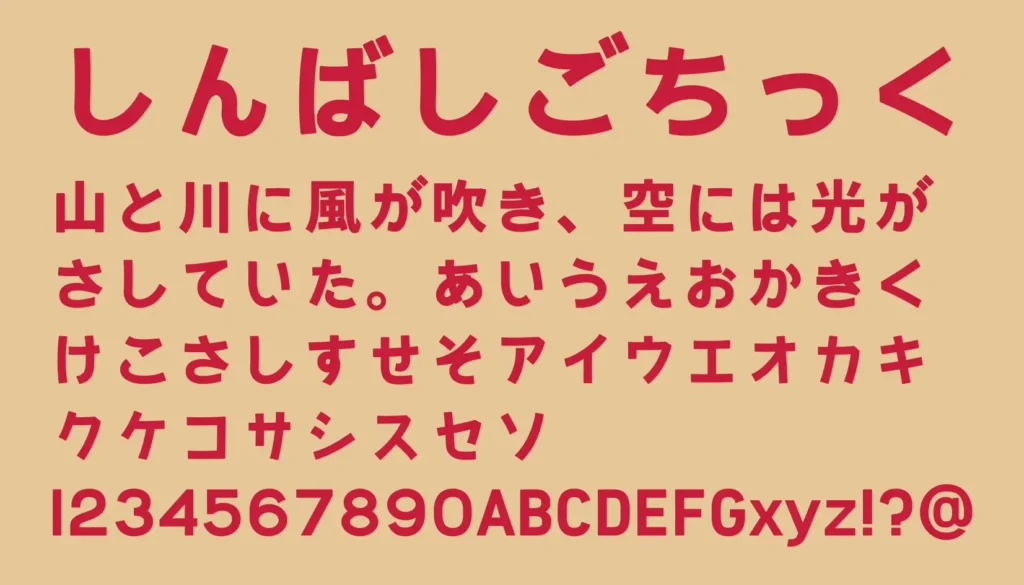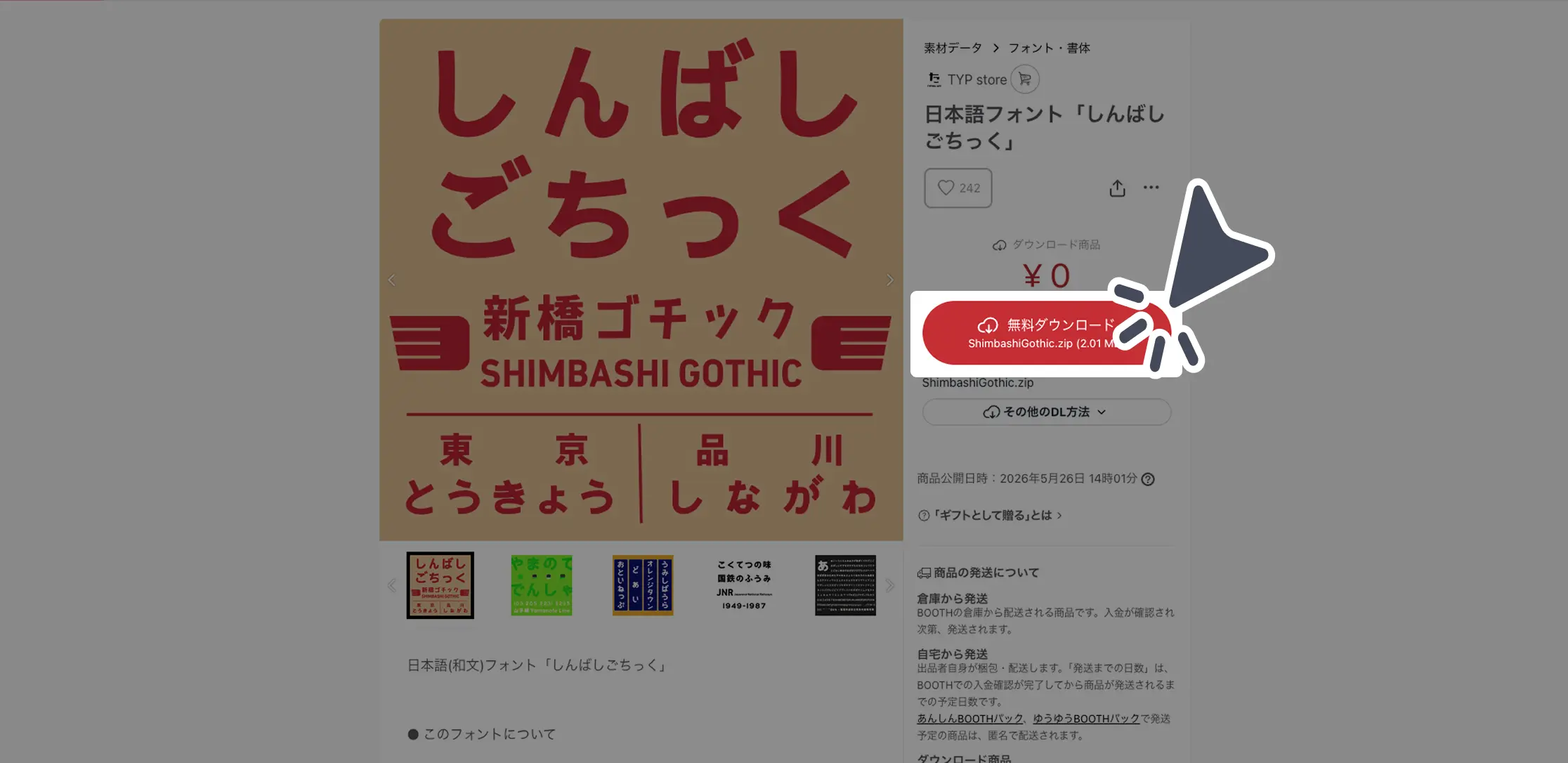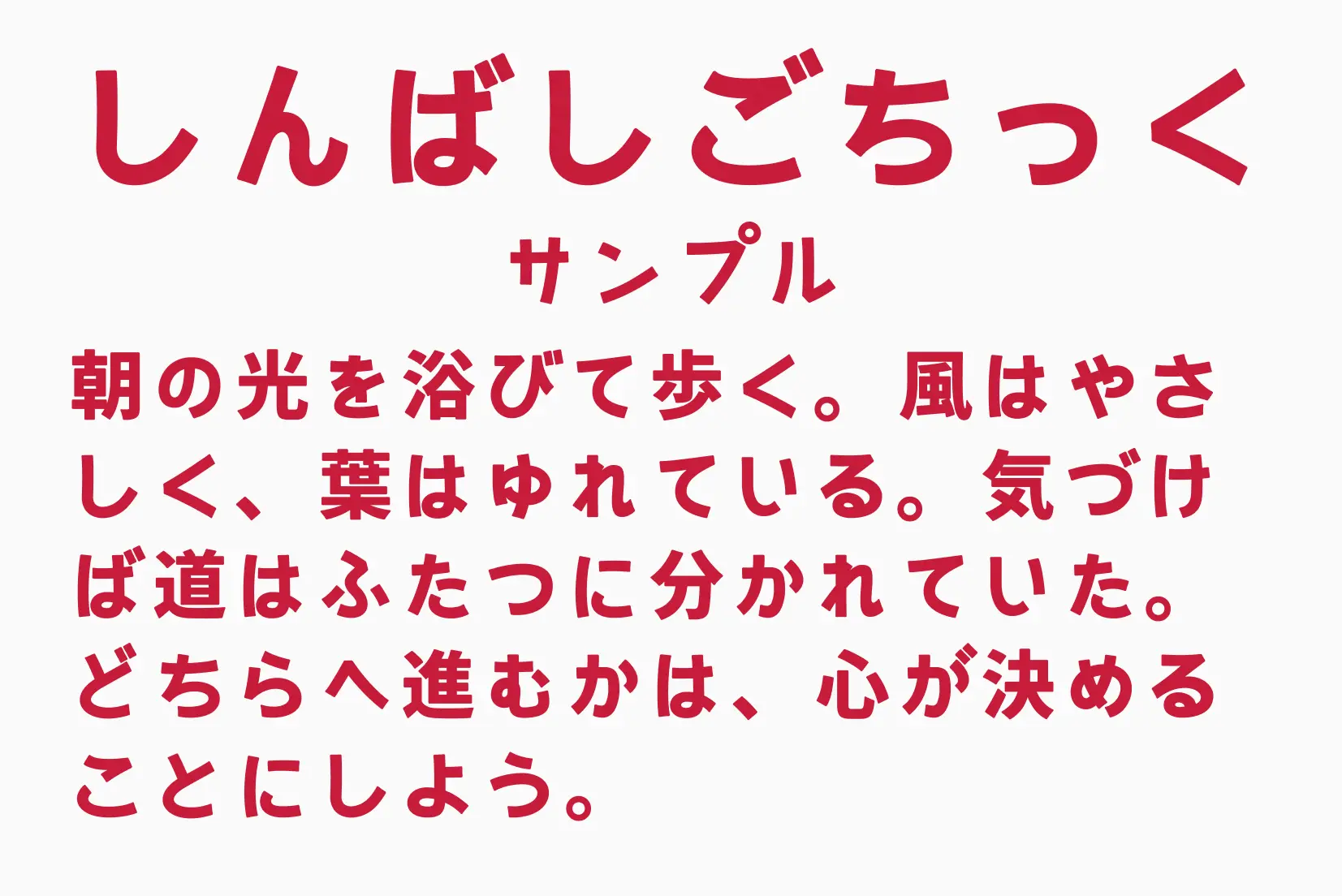
国鉄時代の駅名標や案内サインを思わせるレトロな雰囲気が魅力の日本語ゴシックフォントです。ほどよく丸みを帯びた字形によって、無骨さの中にも親しみやすさがあり、公共サインのような視認性の高さも兼ね備えています。昭和レトロなデザインや鉄道モチーフはもちろん、動画サムネイル、イベントポスター、タイトルロゴなど存在感を出したい場面にもぴったり。懐かしさと実用性を両立した、使いやすいフリーフォントです。
しんばしごちっく